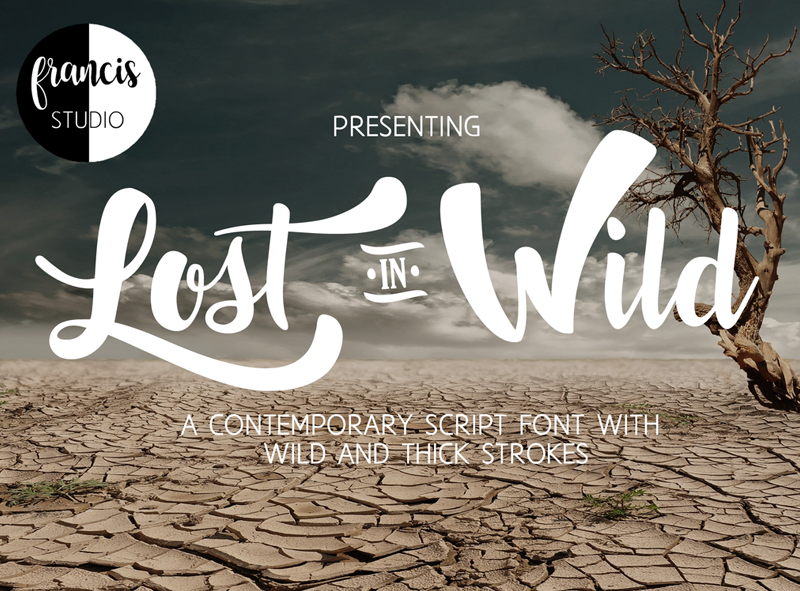
Lost in Wild Font – Download Grátis
Esta fonte é gratuita para uso pessoal. Se você pretende usá-la comercialmente, por gentileza entre em contato comigo por email antes de fazer qualquer utilização. Eu agradeço profundamente à Pexels.com e ao fotógrafo pelo belo fundo que criou meu design. Perfeita para artistas de calligrafia ou designers gráficos, esta fonte oferece uma experiência visual única e encantadora, ideal para criar designs incríveis com estilo autêntico. Adaptada à categoria de Fontes de Escrita Calligráfica, esta é uma excelente escolha para quem busca expressar a beleza da literatura ao marcar seus projetos. A fonte foi criada pelo Studio Francis e incorpora os detalhes do ambiente natural que tanto valorizamos no Brasil. Se você está procurando por uma maneira de dar vida à sua arte ou design, essa fonte é perfeita para capturar a essência brasileira em cada projeto.